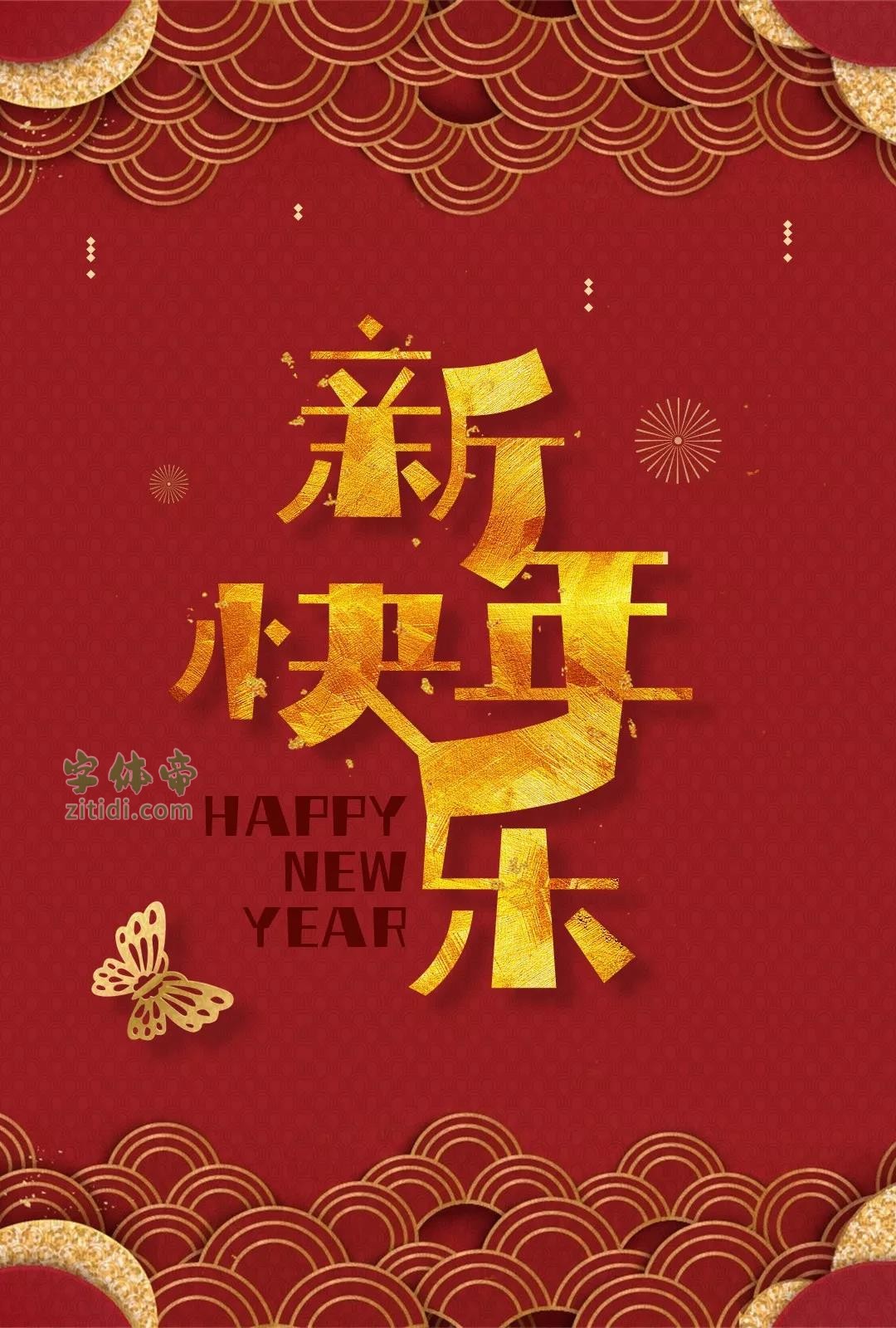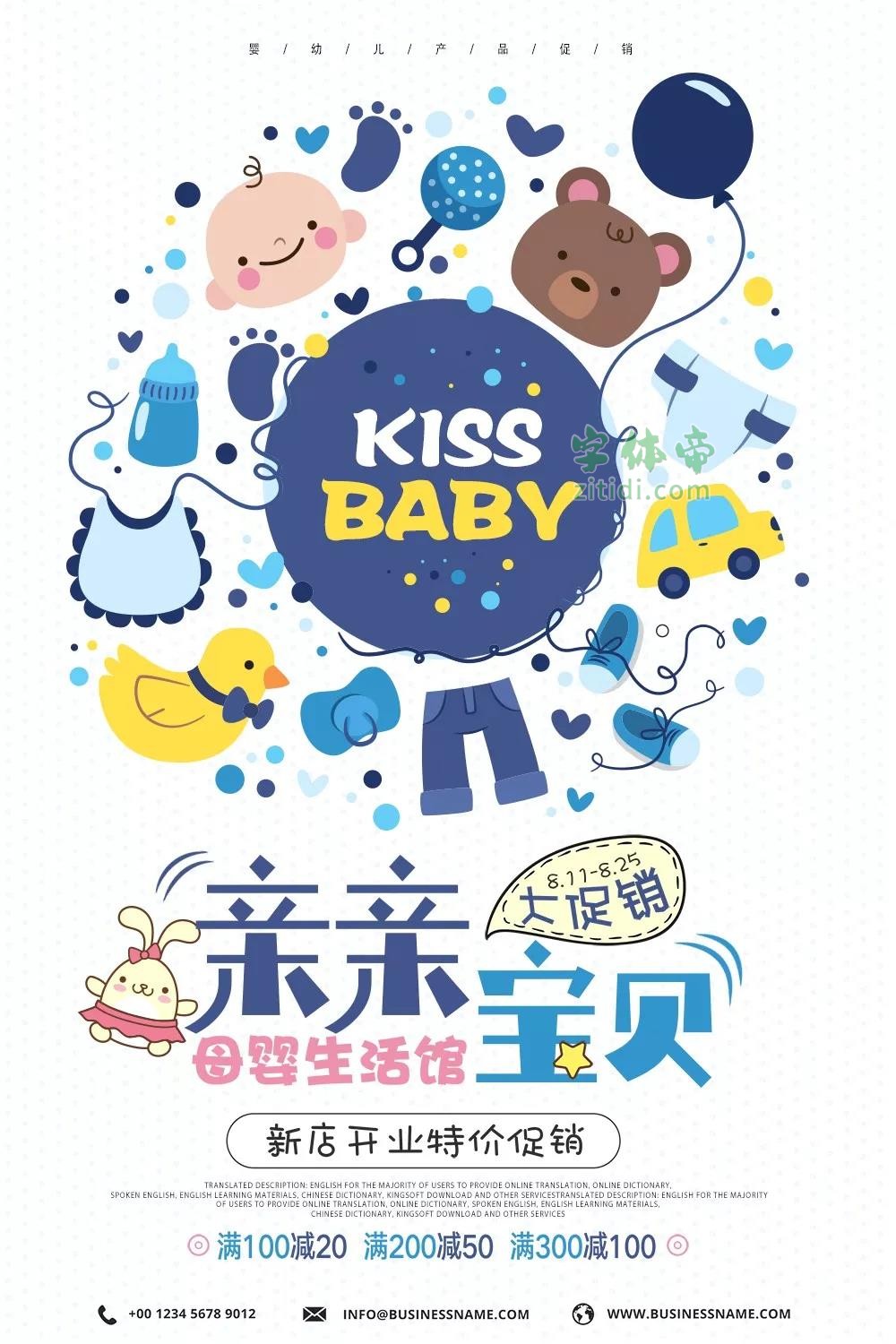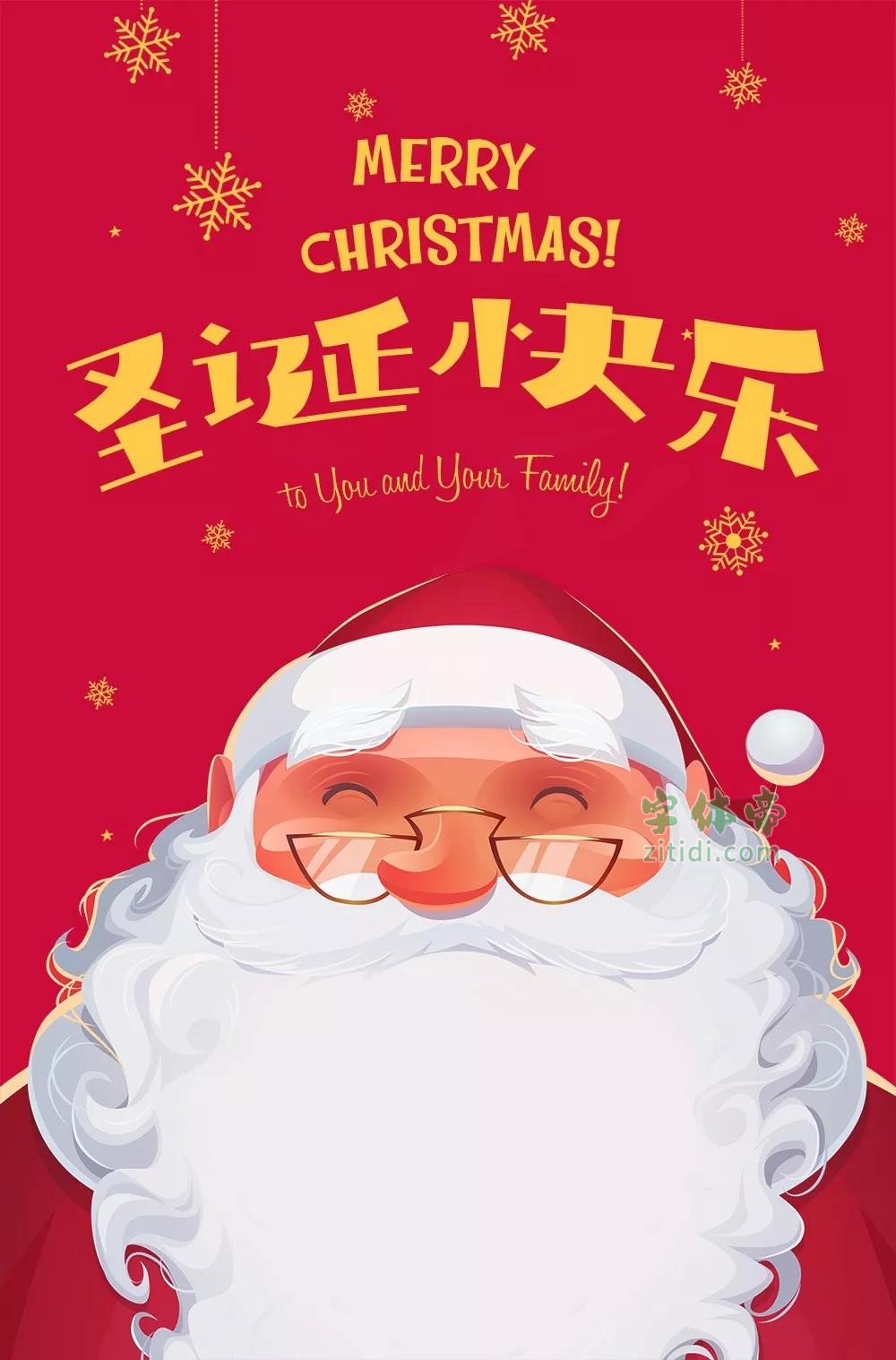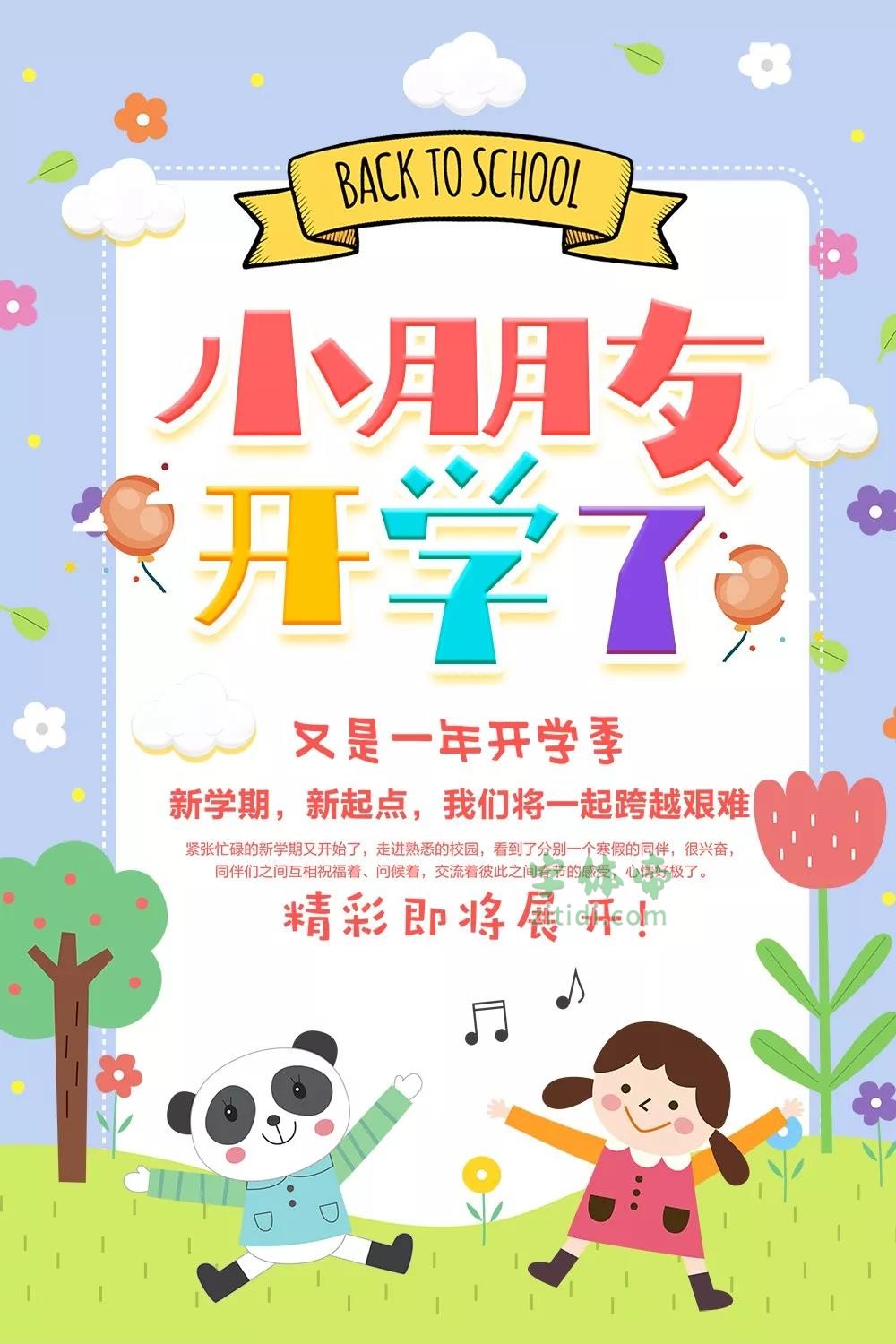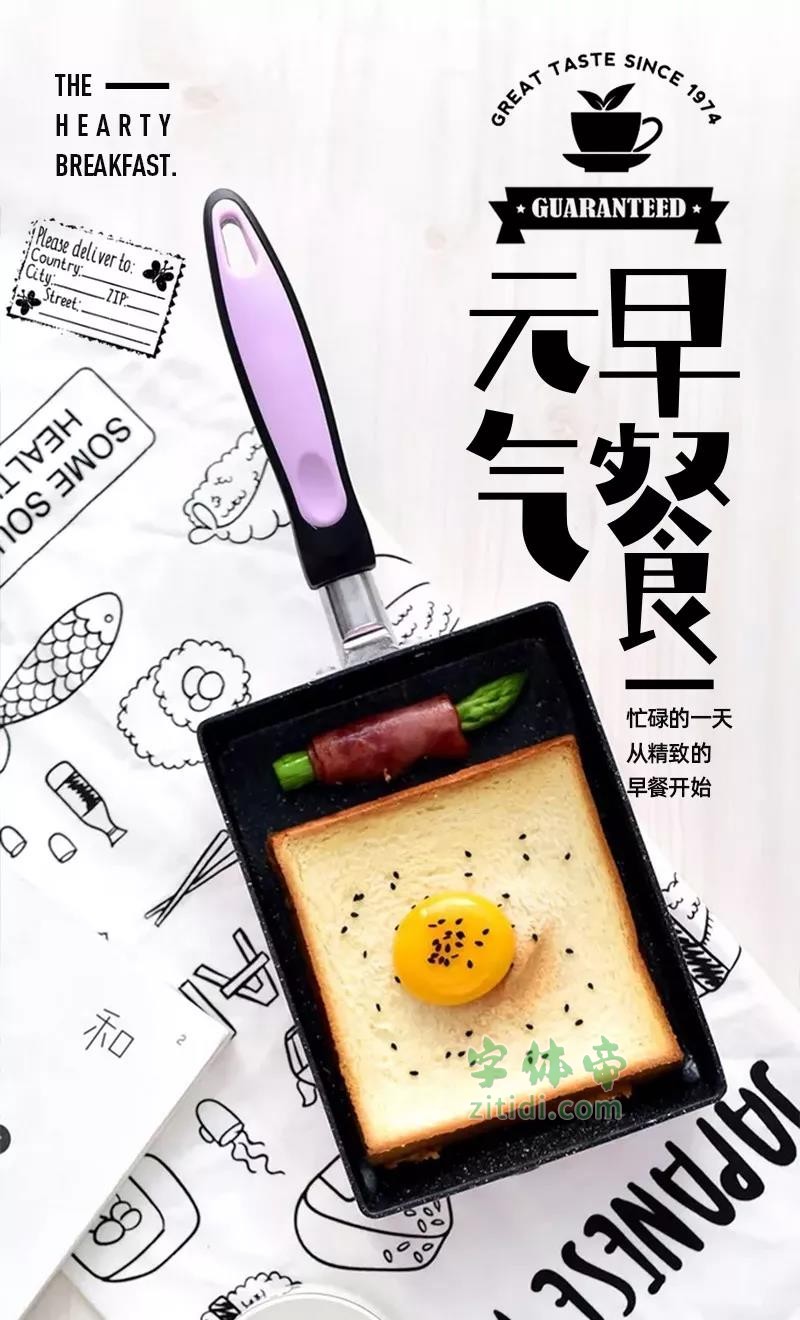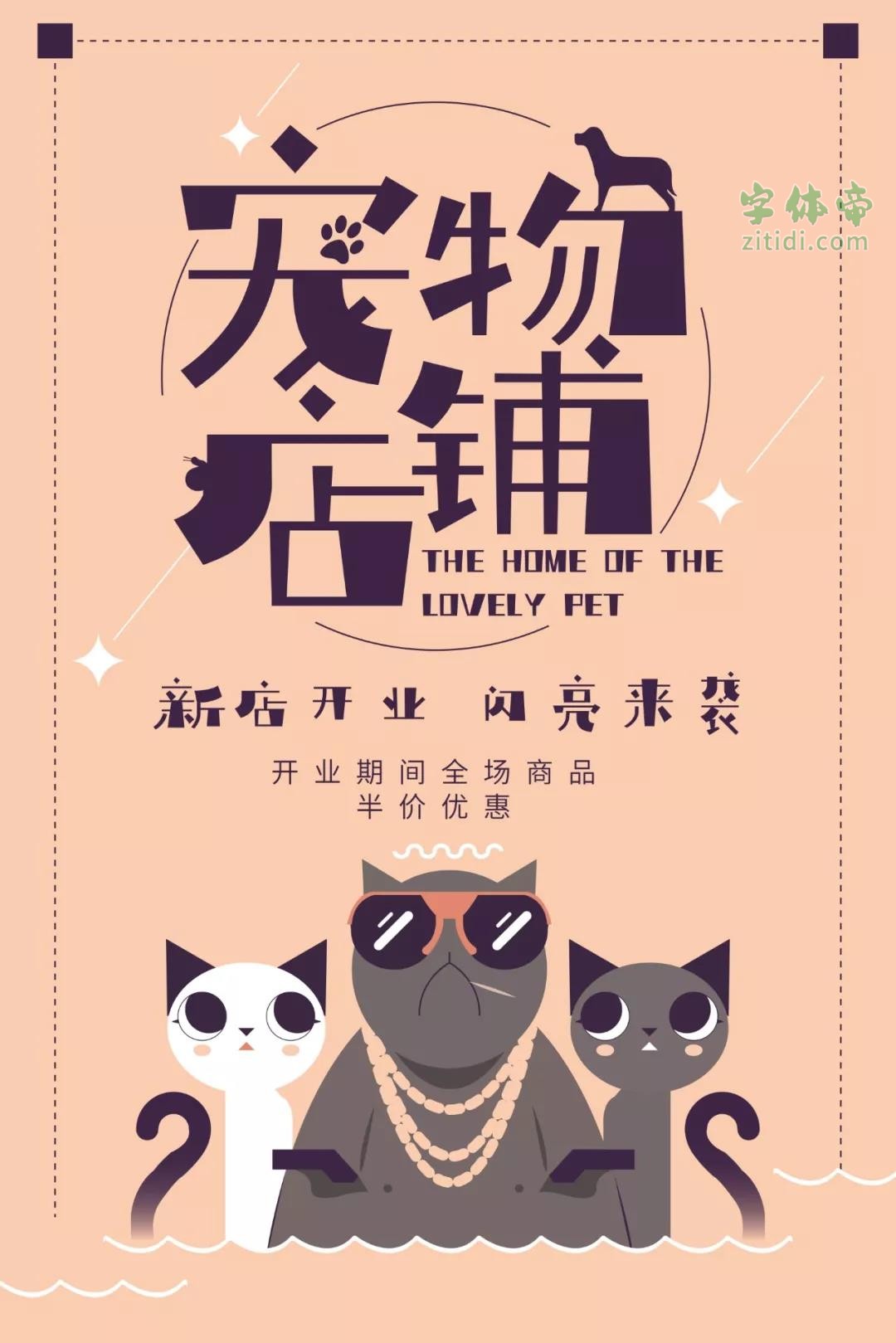
2019年12月5日,在这个特别的日子里,庞门正道第三套免费商用字体庞门正道轻松体正式上线。这款字体是刘兵克字体设计班的学生在自愿的原则下,一共78位学员经过了一年的努力开发的字体。这是一次免费的公益字库的设计,大家都是没有额外的金钱报酬的,仅仅是为了社会公益,社会价值。
庞门正道轻松体字库风格非常可爱蠢萌,带着些许的俏皮的,趣味十足,字形活泼非常适合宠物,儿童等方面的设计。
“庞门正道轻松体”是一款书写很新颖的字体,字体大方,适合各种设计作品使用!欢迎下载!